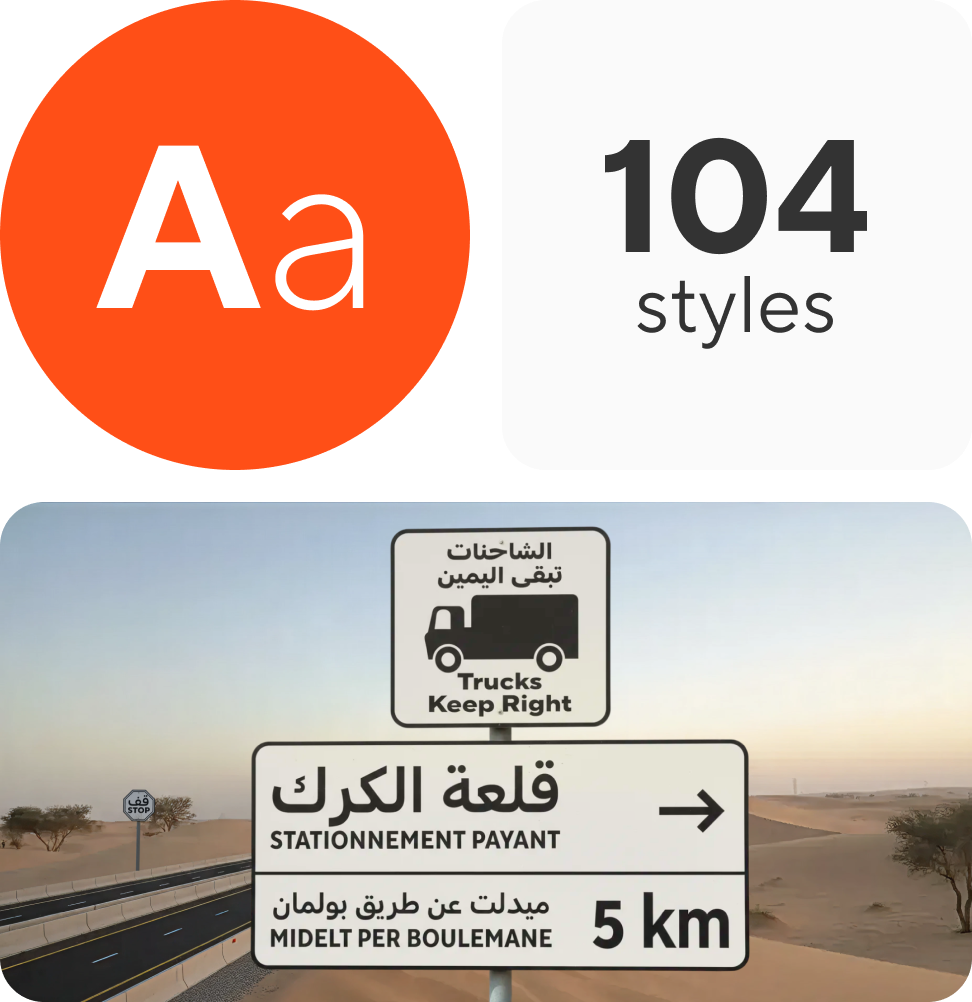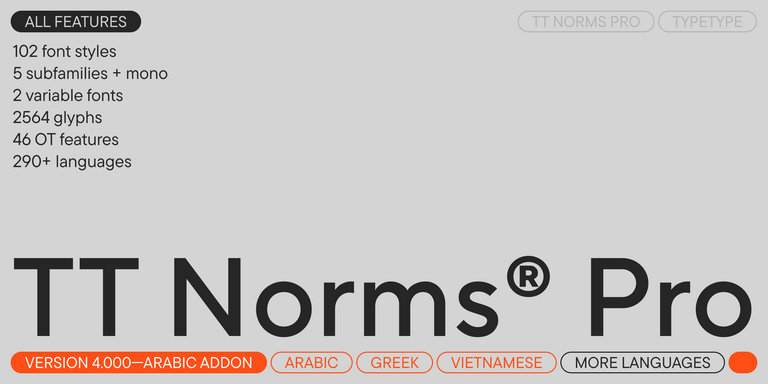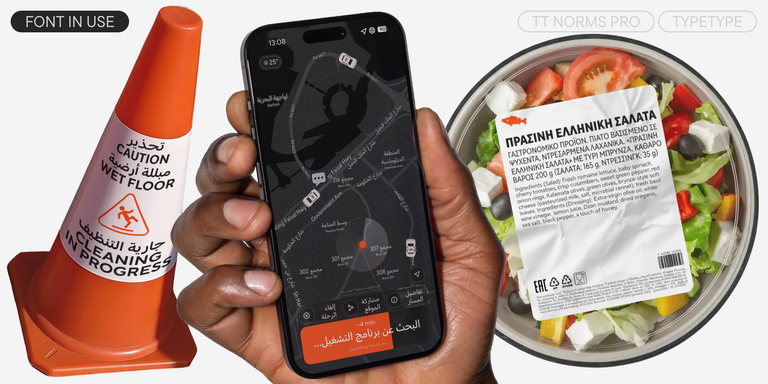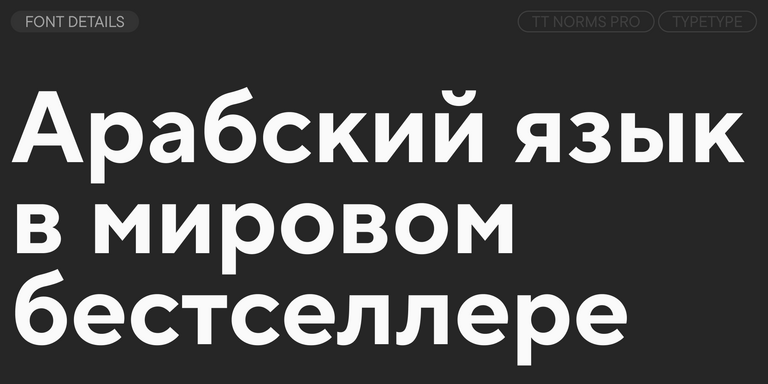
TT Norms® Pro — один из самых востребованных шрифтов студии, выбор известных мировых брендов. Более трёх переизданий за семь лет, первые строчки на MyFonts, десятки кастомизаций. Это «рабочая лошадка», которая станет незаменимой базой любой шрифтовой коллекции.
TT Hoves Pro — скандинавский гротеск с нейтральным, но в то же время узнаваемым характером. Это удобный и функциональный, при этом стильный и эстетичный инструмент для дизайнеров. Такой шрифт позволит вам решать множество разноплановых задач!
TT Supermolot Neue — непобедимое оружие в борьбе за стиль! Это технологичный модульный гротеск с футуристическим настроением и мощным функционалом. Шрифт идеально подойдёт для оформления компьютерных игр и множества других проектов.
TT Firs Neue — сбалансированный гротеск со скандинавскими мотивами. Это выразительный и привлекательный, при этом лаконичный и универсальный в использовании шрифт. Переиздан дважды, чтобы быть безупречным.
TT Rounds Neue — мягкий и дружелюбный шрифт, который умеет быть разным. В тонких начертаниях он выглядит минималистично и нейтрально. В жирных же — «надувается» и округляется, приобретая инфантильные черты.
TT Fors — тот самый шрифт «для всего». Это стильный, лаконичный и функциональный геометрический гротеск с выверенными формами. Его можно использовать и в интерфейсах, и для создания акцентов.